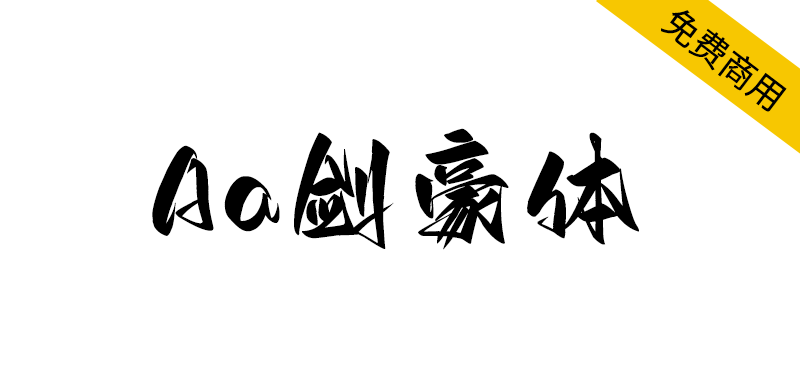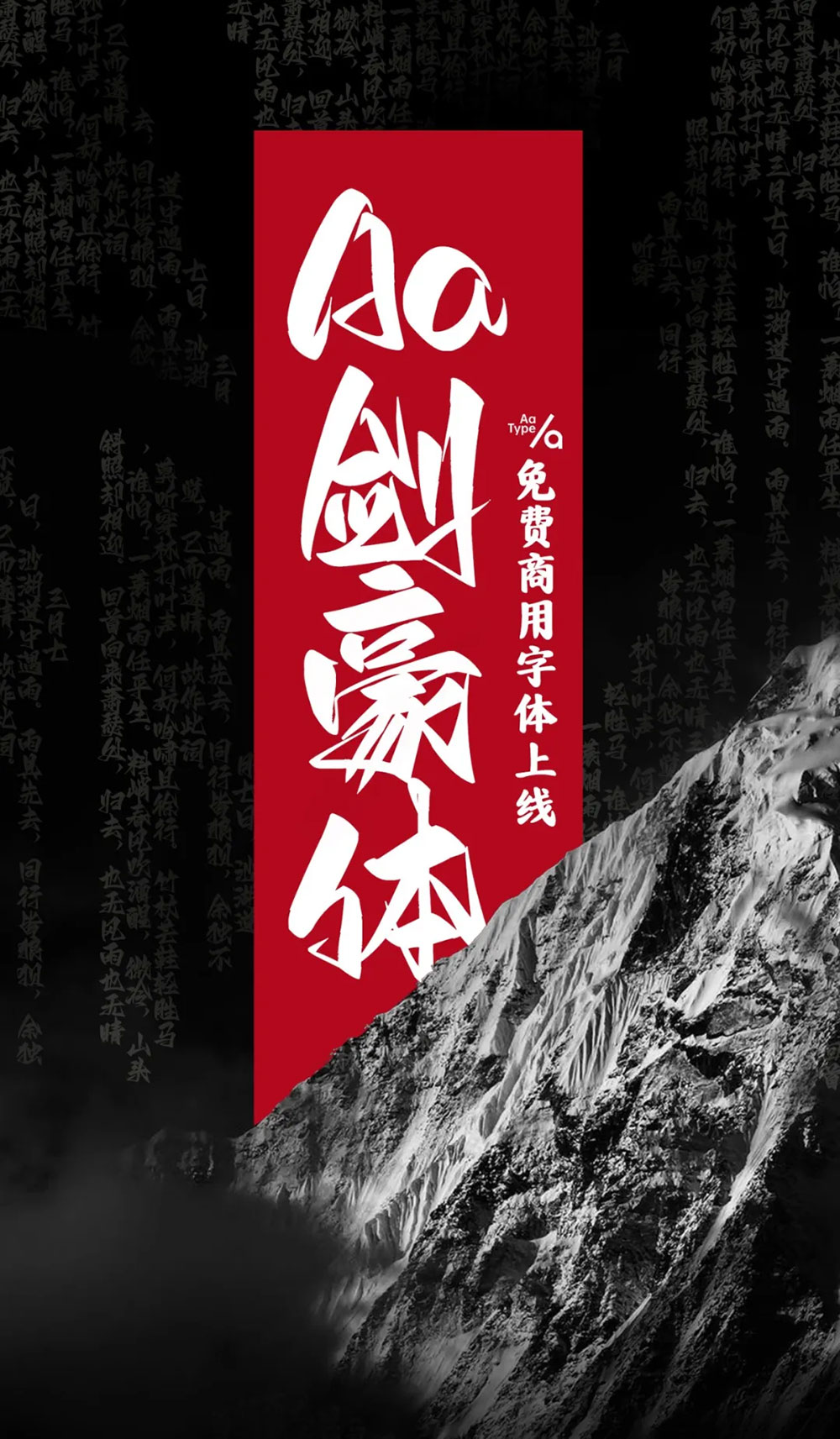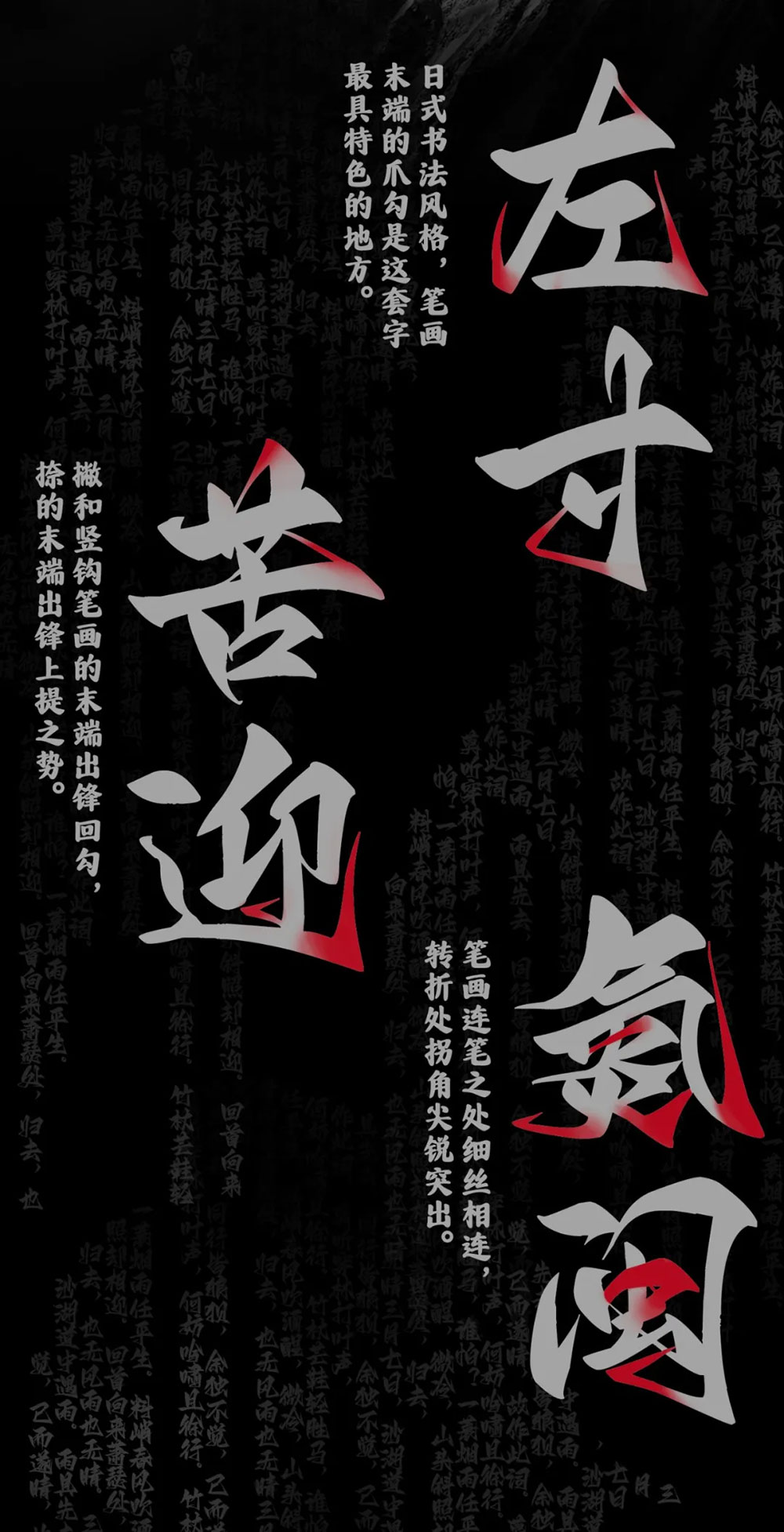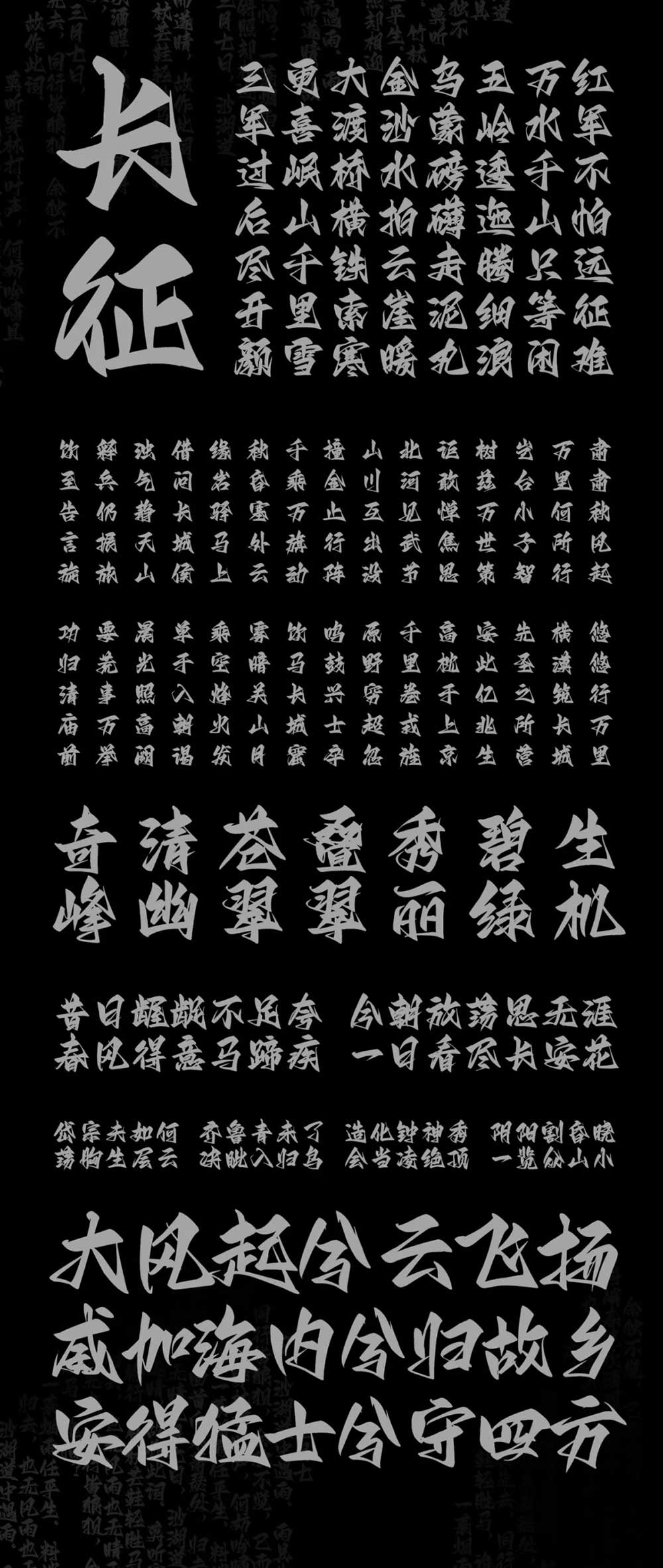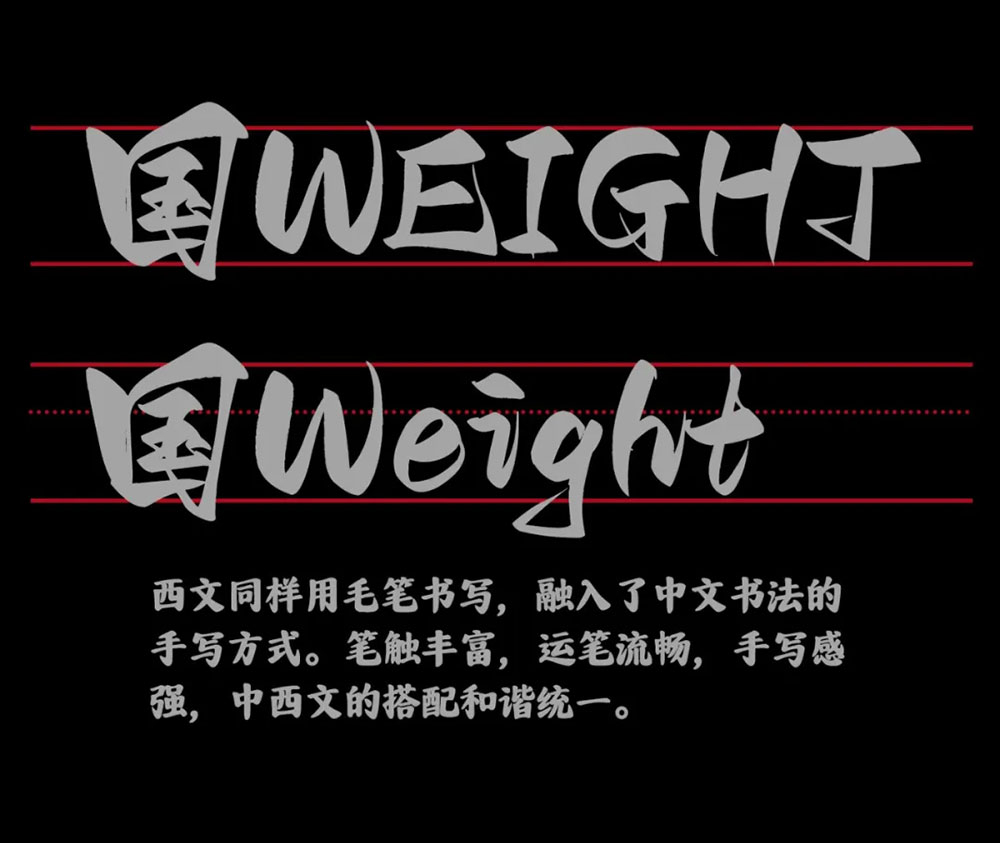
【Aa剑豪体】一款充满洒脱、豪放、霸气、江湖豪气的字体
Aa剑豪体,是Aa字库发布的首款免费商用字体,充满洒脱、豪放、江湖豪气,个性十足,一笔一划锋芒毕露,比其他书法字体更加醒目,极具张力。笔画末端的钩刺极具特色,运笔飘忽快捷,笔迹瘦劲,转折处可明显见到藏锋,露锋等运转提顿痕迹,是一种风格相当独特的书法字体,非常适合应用于适合应用于艺术设计、平面设计、书法字帖等场景。